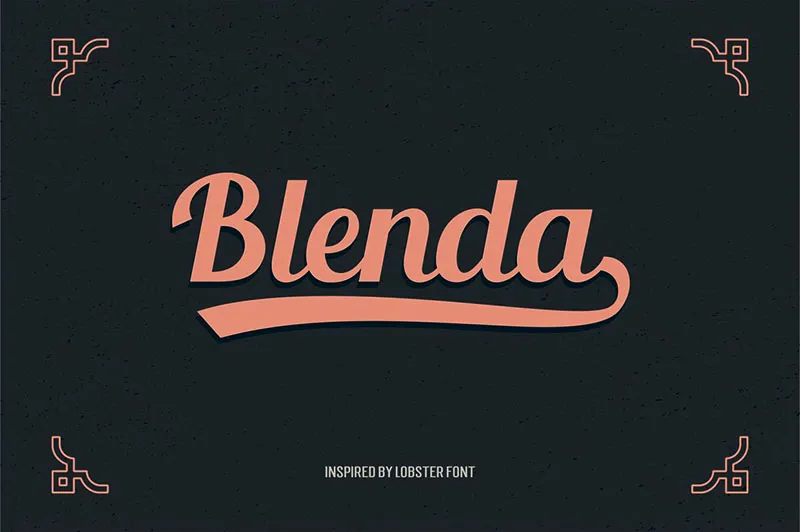
A Blenda Script é uma elegante escolha para designers que buscam uma fonte script vintage e arrojada. Desenvolvida pelo designer Hamilton, esta fonte tem uma forte presença visual e um estilo retro marcante. Inspirada no famoso font de lagosta, a Blenda Script foi criada com o intuito de ser utilizada em diversos contextos como revistas, logotipos, cartões postais e até mesmo em selinhos. Seja para criar materiais publicitários modernos ou design gráfico tradicional, essa fonte atende uma variedade de necessidades. Estamos ansiosos para que você descubra a beleza única dessa Blenda Script; ela certamente enriquecerá seus projetos. Experimente e divirta-se com esta fonte customizada!